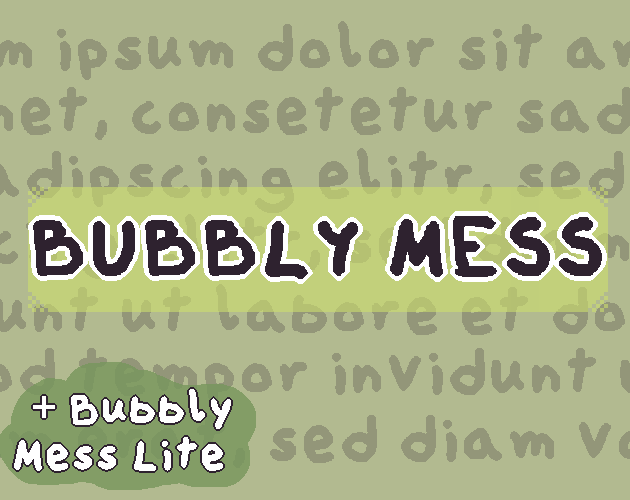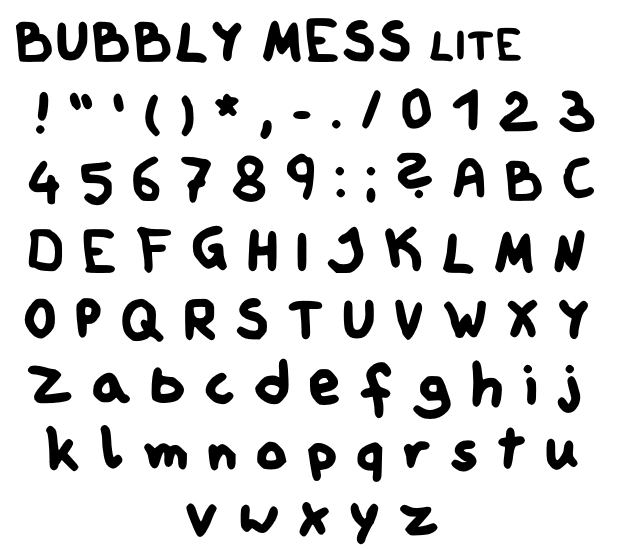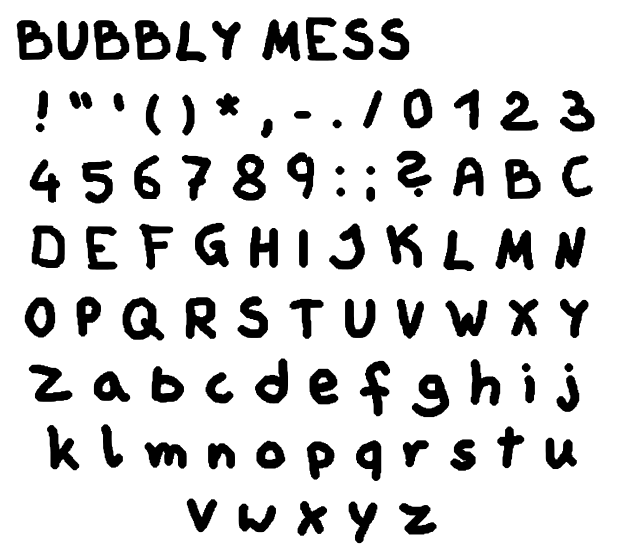
简单的乱糟糟的像素泡泡Bubbly Mess字体素材,“Bubbly Mess”字体完全免费,包含两个版本:“Bubbly Mess”和“Bubbly Mess Lite”,均提供.ttf和.otf格式文件。 Bubbly Mess 比 Bubbly Mess Lite 更圆润一些,像素艺术风格也更浓。 你可以随意使用它们。 声明:本站所有文章,均来源于网络用户收集上传。如若本站内容侵犯了原著者的合法权益,可联系我们进行处理。